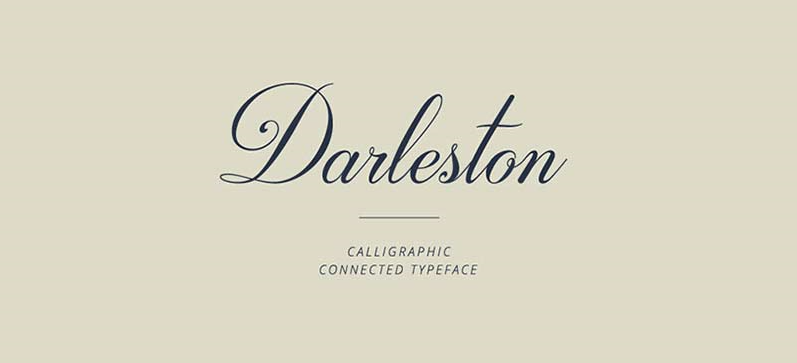
A fonte ‘Darleston Font’ é uma elegante escolha para designers apaixonados por scripts leves e fluidos. Ideal para criações digitais que buscam uma mistura suave de seriedade e originalidade, esta fonte foi projetada pelo designer Hamilton. Ela se destaca na categoria de Script Fonts, com um design arredondado e delicado que evoca sentimentos de conforto e simplicidade. Para usuários pessoais, a ‘Darleston Font’ é livre para uso, oferecendo uma grande liberdade criativa sem custos. Para qualquer aplicação comercial, contate o designer diretamente por questões específicas, como customizações ou grandes quantidades de uso. Esta fonte não apenas enriquece sua obra com um toque único, mas também mantém seu espaço na web livre de problemas legais. Aproveite essa oportunidade para explorar mais designs e recursos criativos da Hamilton, que continuamente surpreende os designers com suas criações únicas e versáteis.